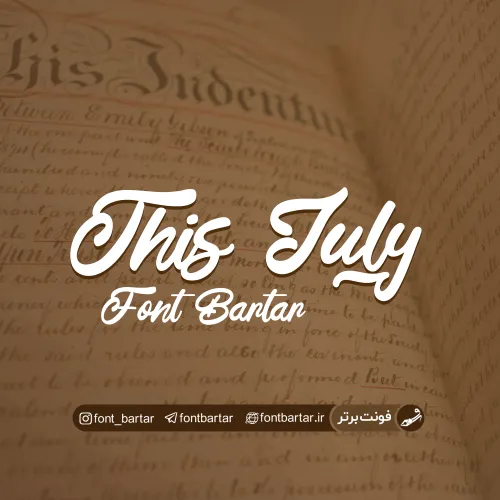
فونت انگلیسی This July
دانلود فونت انگلیسی This July ، فونت انگلیسی گرافیکی با ساختار پیچیده مناسب طراحی تایپوگرافی و لوگو ، پوستر ، بروشور و … ساختار این فونت زیبا بسیار یکدست و خوش فرم می باشد هم چنین این ظاهر زیبا با استفاده بجا و صحیح از المان های خطوط پیچیده بین حروف تکمیل می شود و خروجی بسیار زیبایی را می توان کسب کرد، فونت انگلیسی This July ساخته Syafrizal a.k.a. Khurasan یکی از فونت های مجموعه فونت باندل می باشد که هم اکنون از فونت برتر بصورت رایگان در اختیار شما قرار میگیرد.